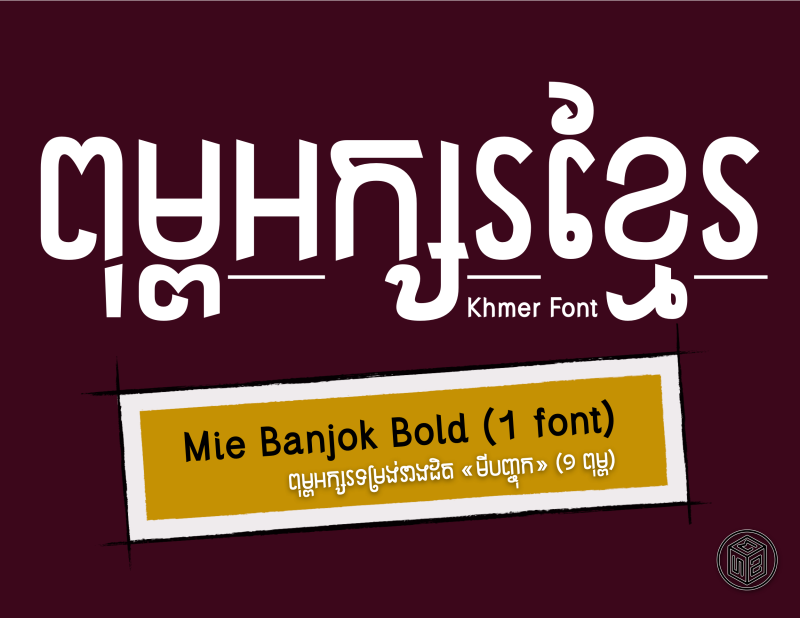
Mie Banjok [Single] Bold (1 font)
Single download file of the classic san serif style Khmer Font - Bold
Mie Banjok គឺជាពុម្ពអក្សរ Opentype ដែលមានការប្រើនៅក្នុងផលិតផលសូហ្វវែរកុំព្យួទ័រជាច្រើនប្រភេទដែលគាំទ្រដល់ OTFs ។ ប្រើក្នុងការរចនាផលិតផល ផ្លាកយីហោ ឡូហ្គោ ក្រាហ្វិចម៉ាឃីត ឬទីណាដែលអ្នកពេញចិត្ត​ បើអ្នកចូលចិត្តរូបរាងនិងអារម្មណ៍ទំនើបនៃរចនាបថថ្មីនៃអក្ខរខ្មែរ។
Mie Banjok is an Opentype font that can be used in a variety of computer software products that support OTFs. Use it in product designs, branding, logos, graphics, marketing, or anywhere you can type in Khmer.